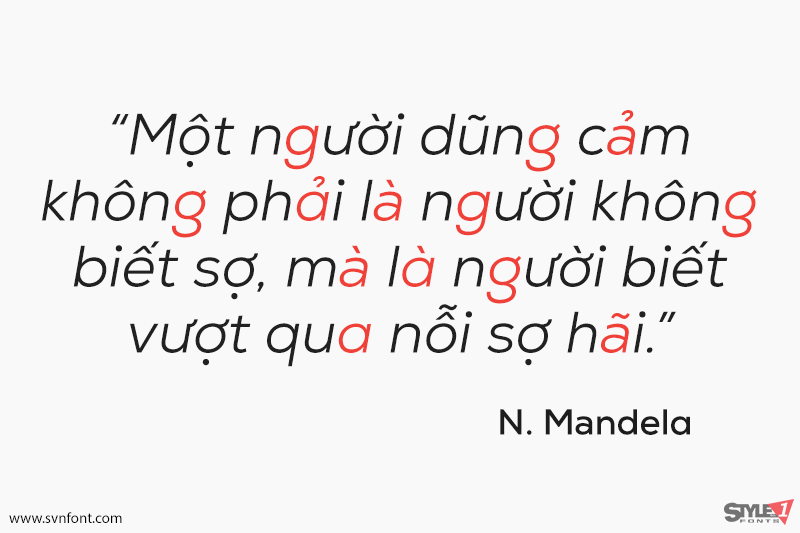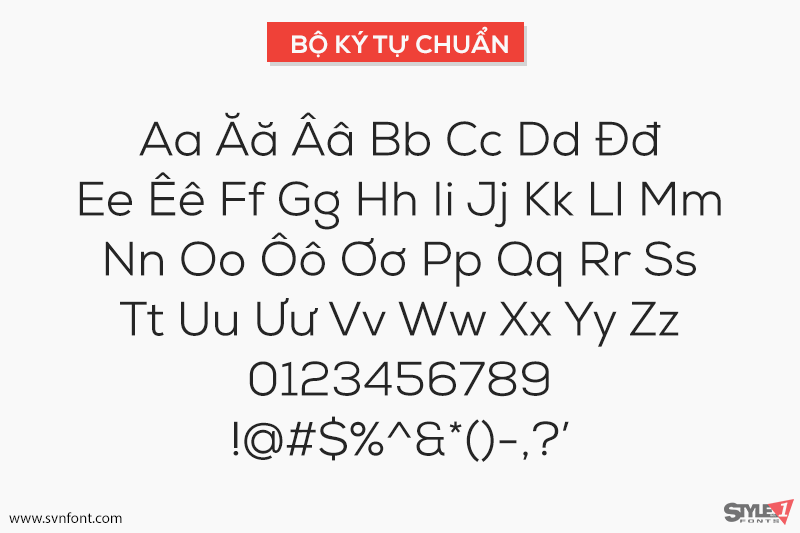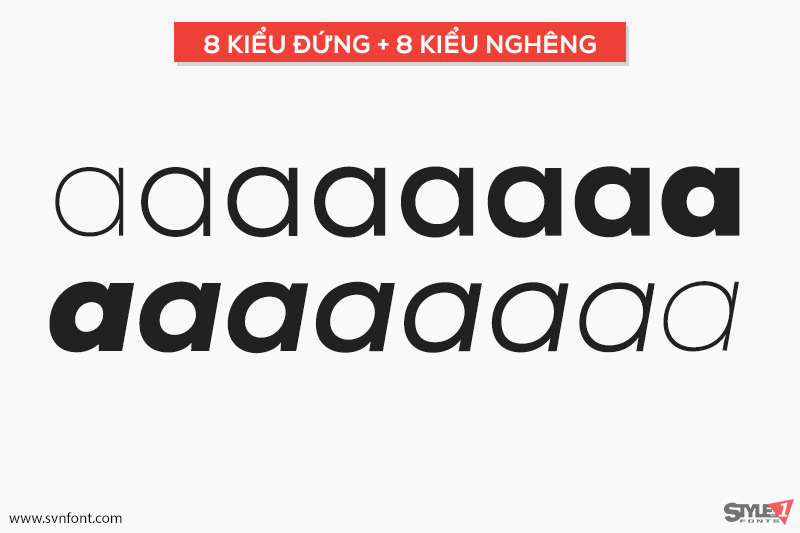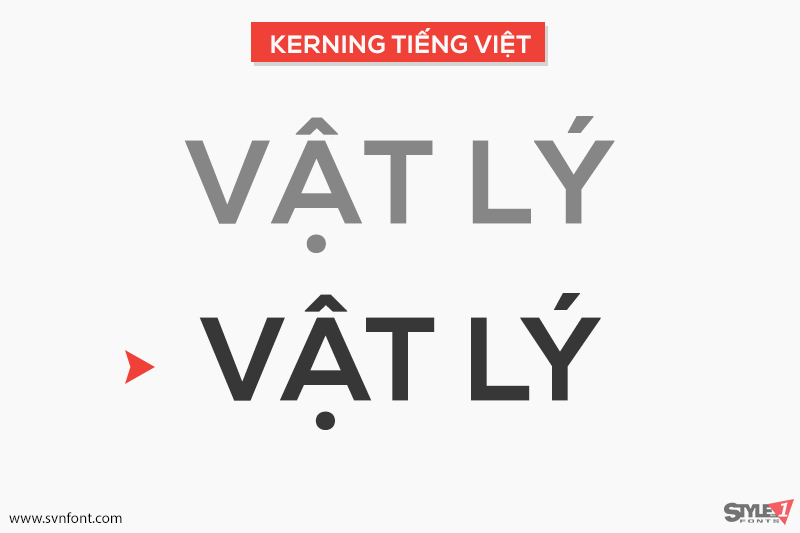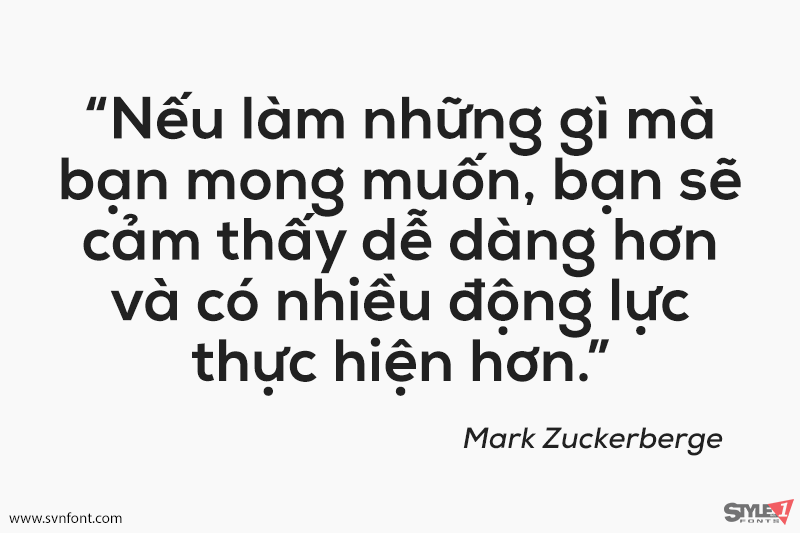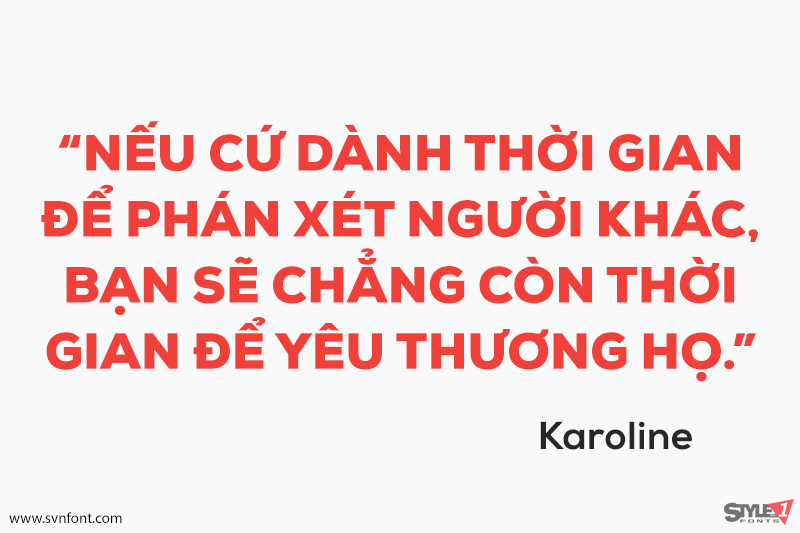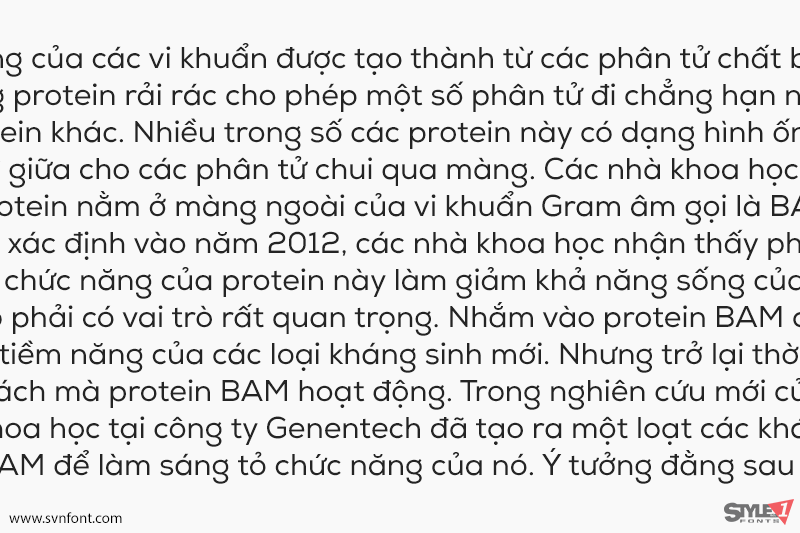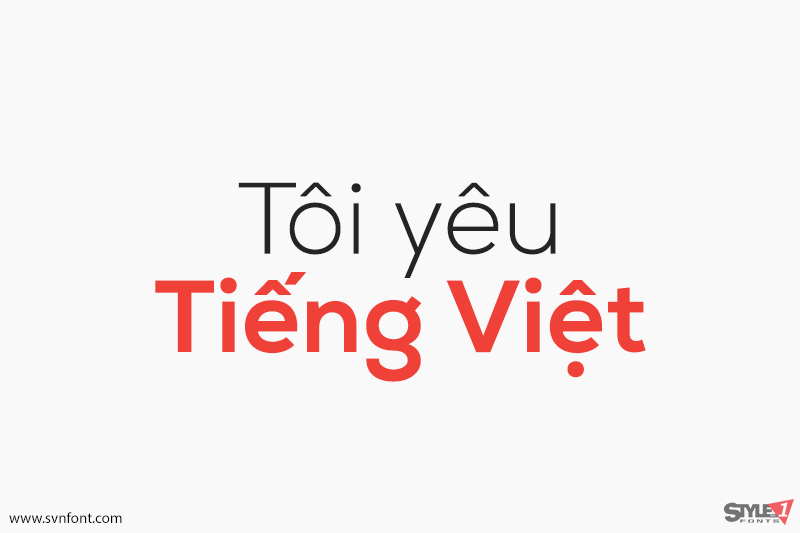
Họ phông chữ Nexa bao gồm 16 kiểu và độ đậm – tám kiểu đứng thẳng với tám kiểu in nghiêng. Nó nổi bật với khả năng dễ đọc tuyệt vời cả trong thiết kế web và in ấn, cùng với các thiết kế hình học được hoàn thiện tốt, tối ưu hóa kerning (điều chỉnh khoảng cách giữa các ký tự), v.v.
Nexa phù hợp nhất cho các tiêu đề ở mọi kích cỡ, cũng như cho các khối văn bản có cả biến thể tối đa và tối thiểu. Các kiểu phông chữ này có thể áp dụng cho mọi loại thiết kế đồ họa trong web, in ấn, đồ họa chuyển động, v.v., và hoàn hảo cho áo phông cũng như các vật phẩm khác như áp phích, logo.
Nhà thiết kế: Svetoslav Simow
Nhà phát hành: Fontfabric